完成小写字母
你可能在你之前见过的字体上注意到,虽然每个字母有其自己的形状,但是他们都互相有联系。通过解构一些字形,你能够得到几乎所有其他字母用来构建的积木。
注意看 c 和 f 的上部结束的相似性:
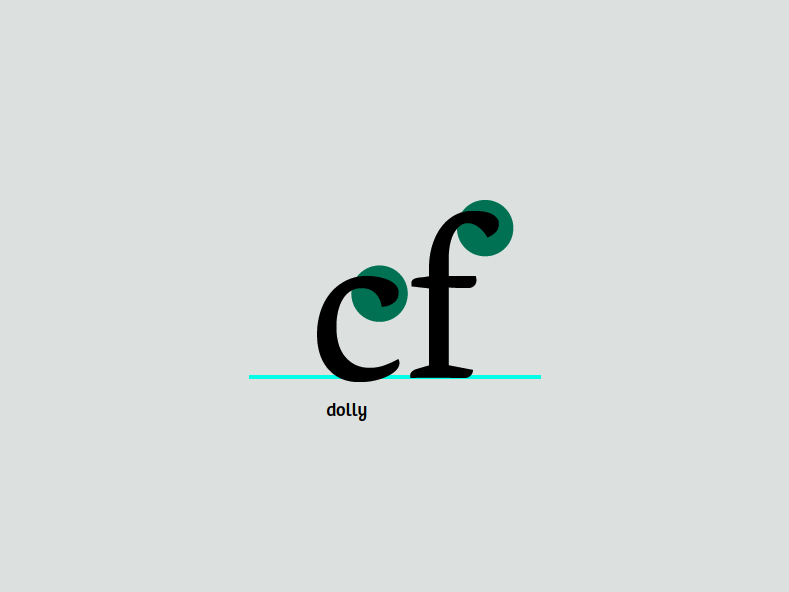
尽管他们巧妙地不同,但是他们的形状表明他们在相同的分组中。结束是字体的区别特征之一,通常在许多字母的形式中反复出现。
但是在模块上过多地依赖模块化来展示设计的标记应该避免–除非这是你想要的样子。
处理其他小写字母
你已经制作了字母“n”。从这个字母我们可以容易地分别通过克隆、拉伸和旋转导出 m、h 和 u。m 和 u 的茎的间距有微妙的改变。u 不仅改变了间距,也改变了衬线。这并不会自动发生;由你来到那推动这几点。
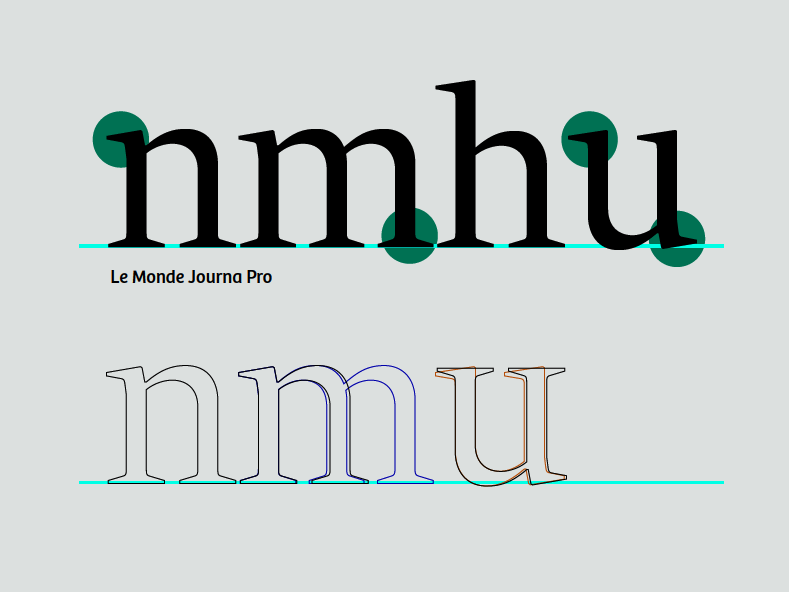
“i”可以由“n”的茎导出。“l”可以由“n”的茎通过一些调整作出。
由 h 和 o 的茎制作 d
在字形窗口的字体视图中通过双击“d”打开字母“d”的字形窗口。在字体窗口中复制“o”并粘贴进字母“d”的字形窗口。然后为“h”做同样的事情。在这时你可以删除h中不准备使用的一部分。把剩下的部分摆放在一起,这样他们像一个 d 一样。
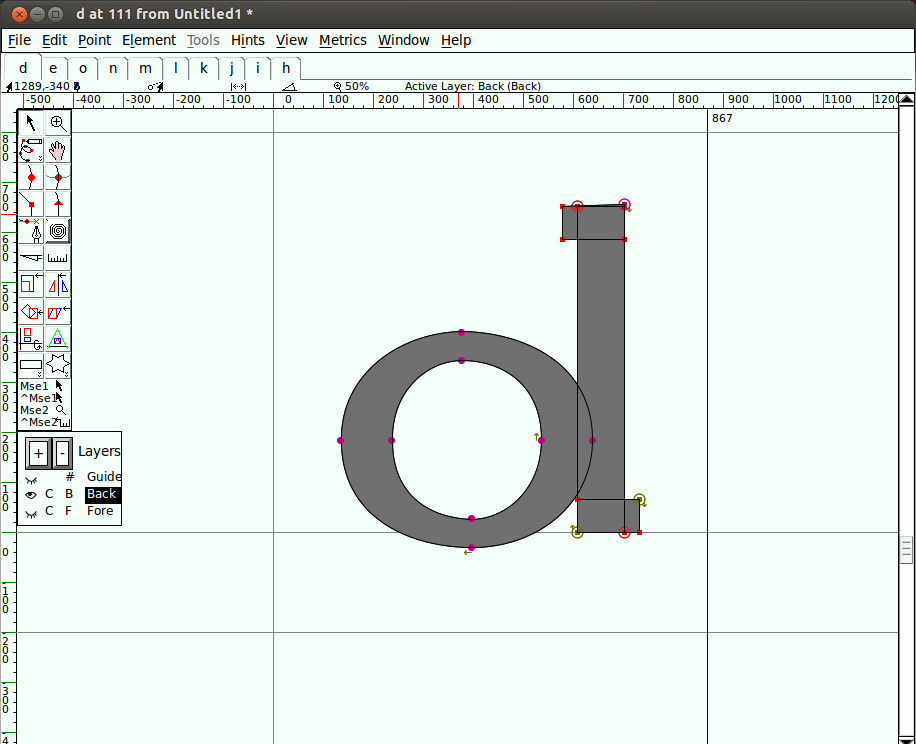
很明显这里还有一些工作需要做。我们将做出一些调整。让 o 的右边变窄,这样可以与茎匹配。
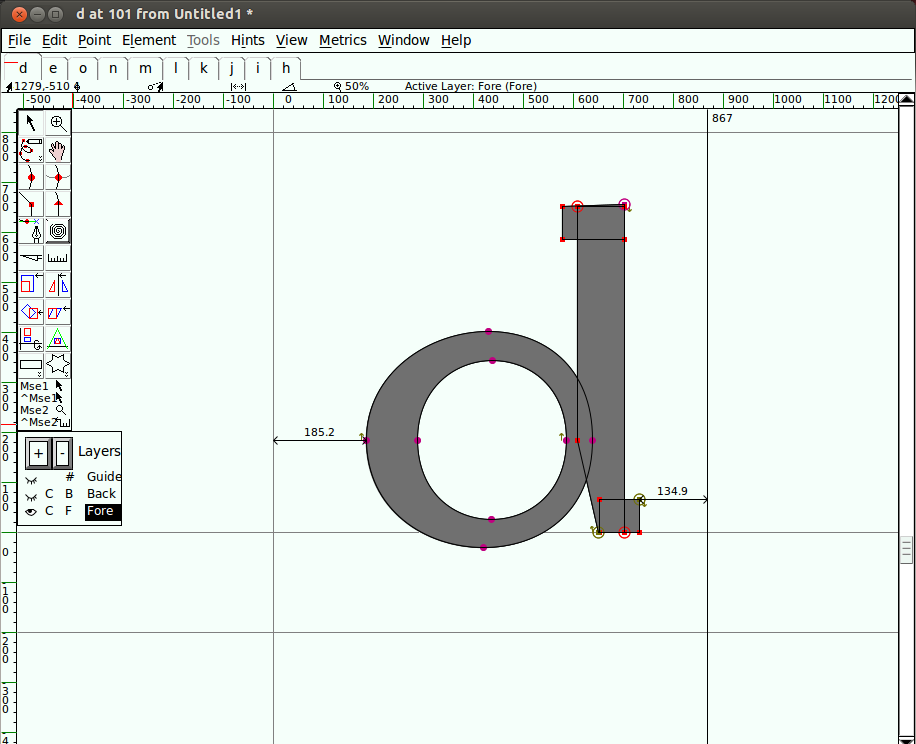
为了改善视觉间距并让图形看起来更平衡,通过在茎上添加一个点,让地步指向右边,在衬线上腾出地方来。
下面是最初的图形和新图形的覆盖图。
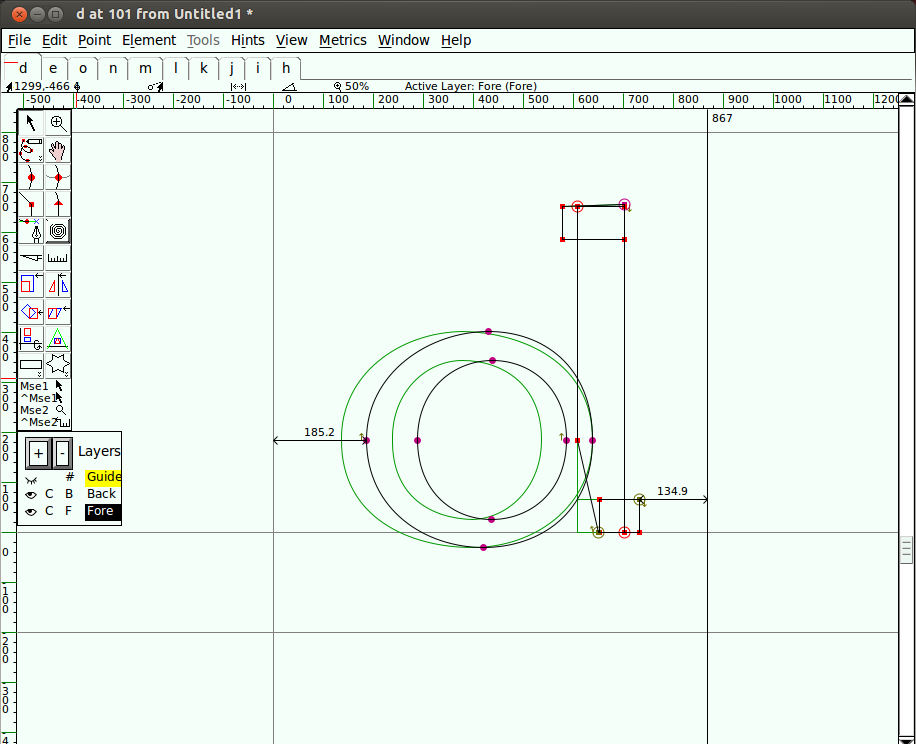
现在你知道该如何组装已有的部分,你可以制作其他类似的字母。要时时注意使得每个字母独特但仍处在一个字体家族中的微妙之处。
导出 b、p 和 q
现在你可以通过翻转和旋转制作出合理的 b、p 和 q。再次提醒注意每个字符的衬线和对比的如何不同。你的字体不必完全相同地做这件事,但是这是你应该思考的事情之一。
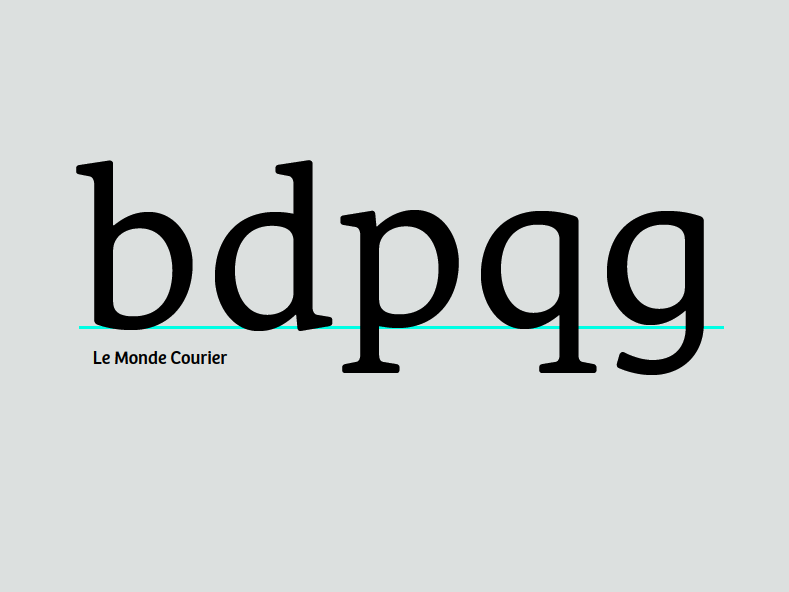
制作 g
你可以从 q 开始,拉伸和修改尾部来制作单个弧线(bowl)的 g。没有形状看起来接近双眼的 g。双眼的 g 通常需要细一点,这样与其他字母放在一起的时候看起来没错。
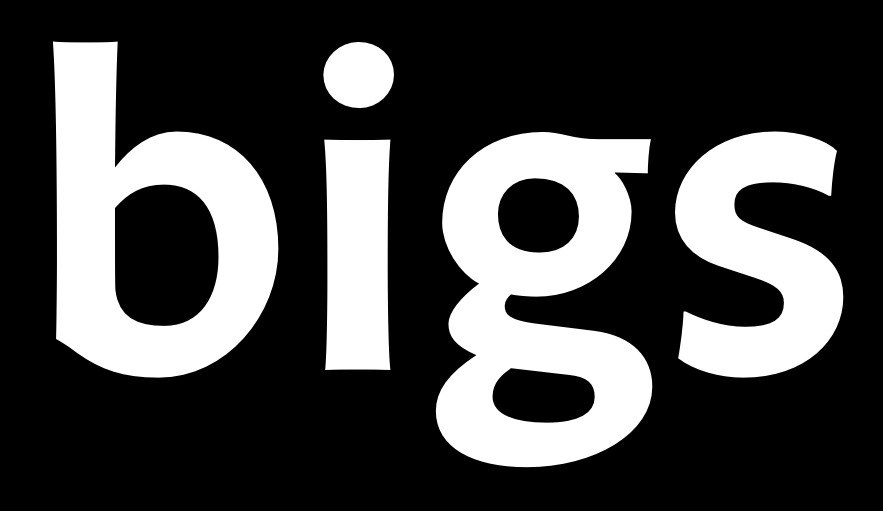
朝 f 和 t 迈进
t 有一个头部,但是通常比其他小写字母的头小。通过比较发现f比其旁边的字母高很多并且经常侵占其空间。他们都有横着交叉的条形,这些条形有相同的高度、宽度和厚度。你经常可以从一个复制到另一个。
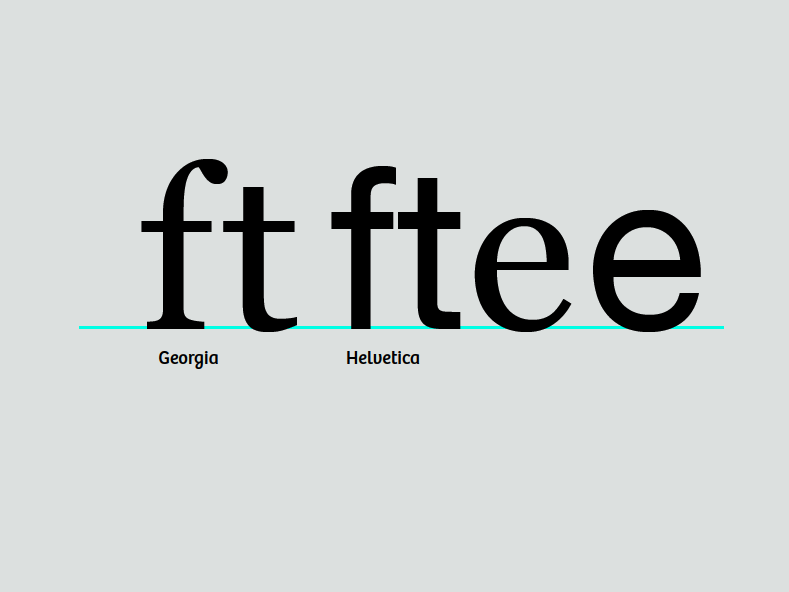
现在制作 e
e 将会宽松地基于 o。e 的交叉条形比 t 的更低,但是有相同的厚度。e 下部的钩子可以由 t 的底部提供。
从 e 到 c
从 e 创造 c 可能需要删除交叉条形并在顶部添加结束。c 的上部的结束可以与其他字母的上部结束类似,比如 a、f 和 r。c 的结束也可以形成 s 的基础。e 也可以影响 a 的比例。
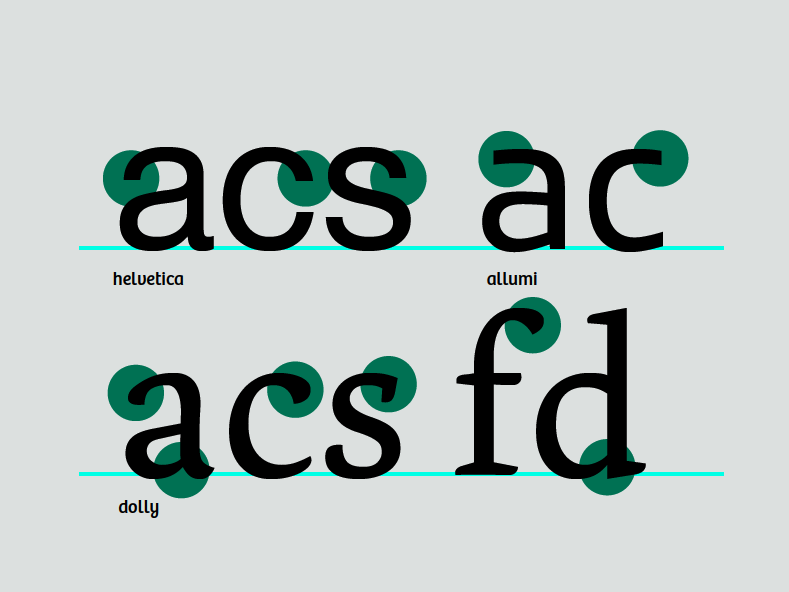
v,w,x,y 和 z
这些字母有一点难,因为他们没有与其他字母相关的形式。这意味着你不得不直截了当地绘制 v。绘制下面的比划与你的其他字母的粗的茎一样粗,让你的上面的比划像你的其他字母的细的茎一样细。一旦你有了 v,你就有了 w 和 y 的基本计划。对于 x 和 y,在补偿斜线和交叉斜线的错觉时,聚焦在匹配设计的其他部分的对比。